那麼,您來對地方了! 在這篇博文中,我們將探索 Monster Fonts 的世界,以及它們如何為您的設計增添額外的魅力。
現在,您可能想知道,Monster Fonts 到底是什麼? 他們會為我的特定項目工作嗎? 別擔心,我們已經為您找到了所有答案。
Monster Fonts 是大膽、非傳統且引人注目的字體,可以立即將您的設計作品從普通變為非凡。
將它們視為傳統字體的叛逆無畏的兄弟姐妹,隨時準備打破規則並發表聲明。
這些字體有各種風格和變化,從怪異和令人毛骨悚然到俏皮和異想天開。 因此,無論您正在進行什麼類型的項目,都有一款 Monster Font 能夠完全滿足您的需求。
在這篇文章中,我們將分享有關 Monster Fonts 的必知信息。 從哪裡可以找到它們,如何選擇合適的,甚至還有一些將它們與其他設計元素配對以獲得最大影響的專業技巧。
因此,準備好發現一個全新的排版世界,它將把您的設計項目提升到一個新的水平。 興奮的? 我們當然是! 讓我們立即開始探索 Monster Fonts 的驚心動魄的領域。
最佳高級怪物字體
希望將您的設計項目提升到一個新的水平? 別再猶豫了! 在本節中,我們將展示最優質的 Monster 字體,它們必將提升您的設計。 不要錯過這些令人難以置信的字體 - 今天就查看它們並獲得靈感!
石斑魚怪物
Grouper Monster 是一種粗體腳本字體,擁有一系列吸引人的功能。 其獨特的風格肯定會激發平面設計師的靈感,以增強他們的項目。
使用這款 Google Monster 字體,您可以為任何設計增添創意和個性。 其大膽的本質使其成為標題、徽標和其他引人注目的元素的絕佳選擇。 準備好與石斑魚怪物一起釋放你的創意怪物!
可愛的怪物
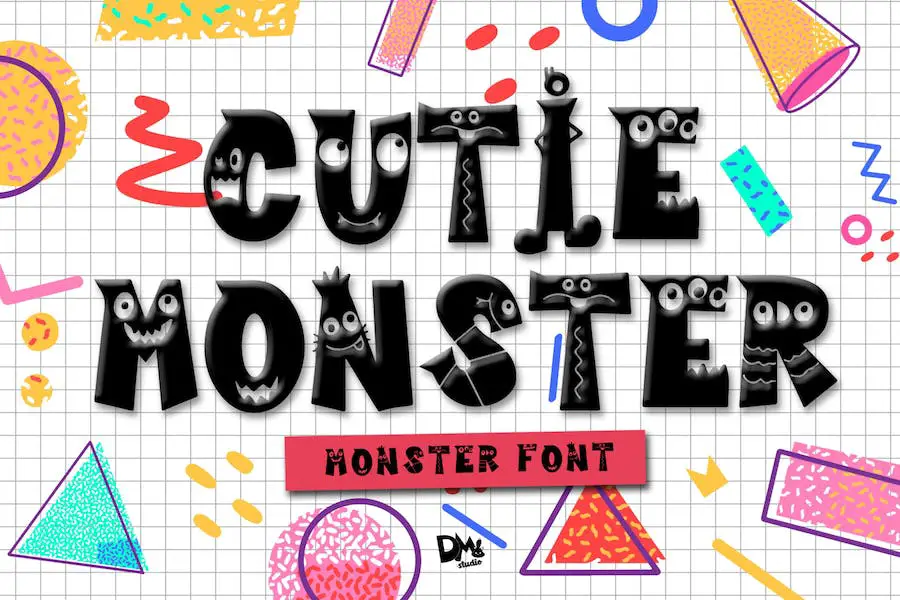
Cutie Monster 是一種令人愉悅且活潑的怪物字體,可為任何設計項目增添額外的魅力。 無論您是創建派對卡片、橫幅還是壁紙,這種字體都會帶來俏皮且富有表現力的氛圍。 它也非常適合製作手工藝品和宣傳材料。
最好的部分是它非常易於使用,不需要任何額外的軟件。 Cutie Monster 專為滿足您的創意需求而設計。
這款 Adobe Monster 字體有大寫和小寫兩種形式,允許您混合搭配,為您的設計創造完美的外觀。 憑藉其可愛有趣的風格,它添加了獨特而引人注目的元素,一定會給人留下深刻的印象。
Cutie Monster 的多功能性使其適用於從兒童材料到專業設計的各種項目。
友好的怪物
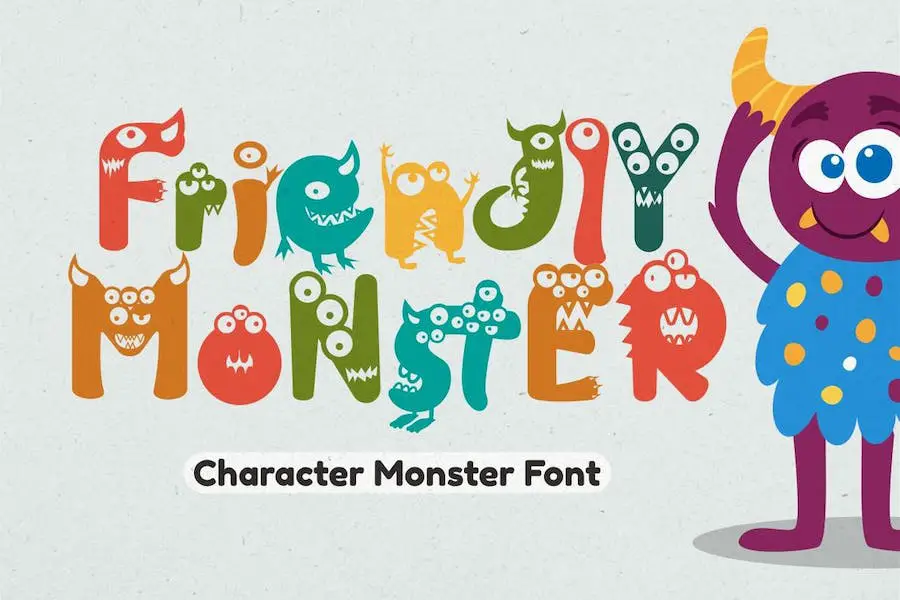
Friendly Monster 是一種角色怪物字體,可為您的設計項目增添歡快的感覺。 它非常適合海報、服裝、徽標、引言、專輯封面、書籍、名片等。
儘管其主題令人毛骨悚然,但 Word 的 Monster 字體具有嚴格的風格,使其易於閱讀和應用。 無論您是在尋找可愛、可愛還是友好的東西,Friendly Monster 都能讓您的設計脫穎而出。
怪物Demit
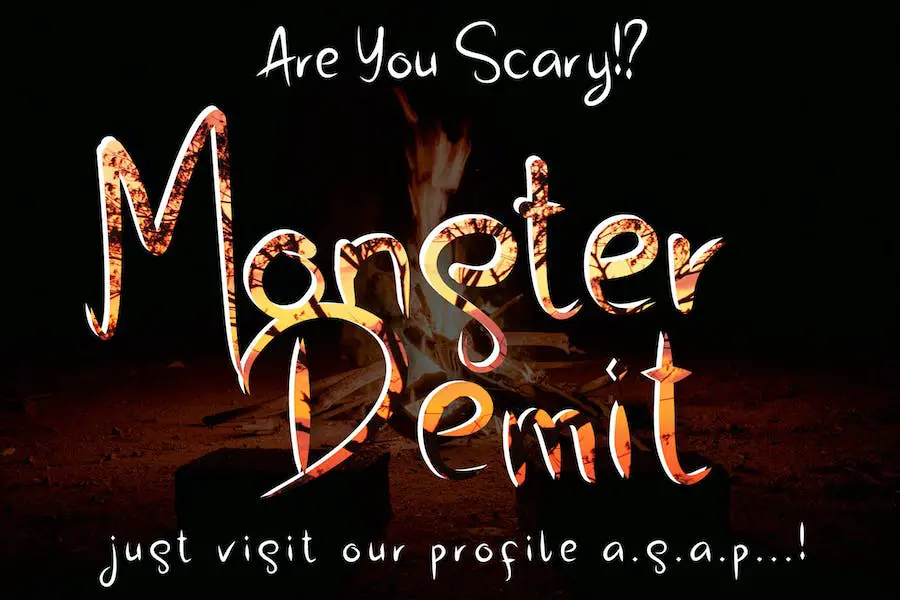
Monster Demit 是一種提供獨特而自然的觸感的字體,可以提升任何項目的水平。 這種字體被設計為可讀、優雅、時尚、吸引人,並且非常用戶友好。
Monster Demit 憑藉其時尚和專業的美學,是在品牌、設計、婚禮請柬、攝影、簽名、標誌設計、專輯封面、名片、報價和各種其他設計項目上創建水印的完美選擇。
無論您是專業的圖形設計師還是希望增強項目視覺吸引力的人,這款 Monster Fonts for Canva 都是一款不會讓人失望的字體。 它的多功能性和易用性使其成為您的字體集合的絕佳補充。
頑皮的怪物
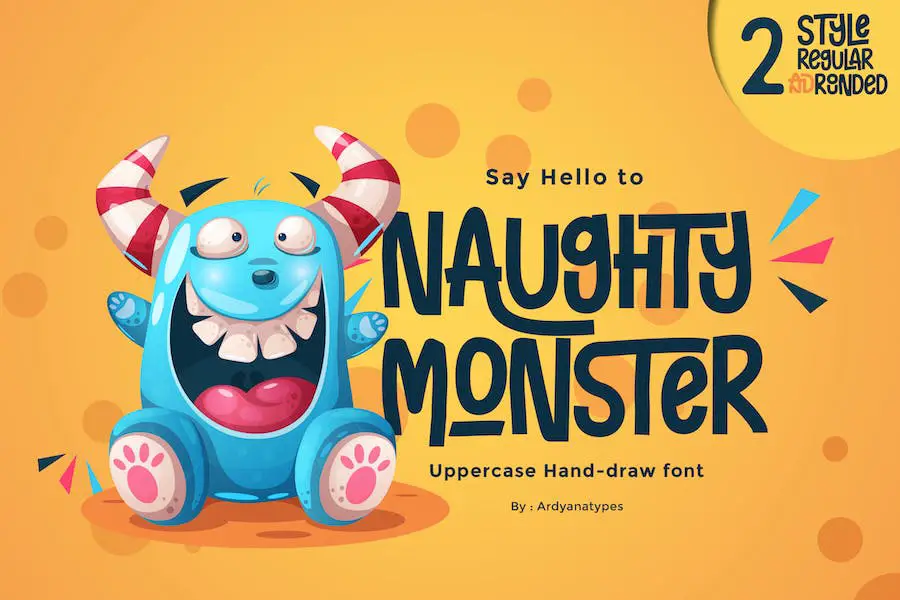
隆重推出 Naughty Monster,這是一種古怪而有趣的字體,旨在增強您所有的圖形設計項目。
憑藉其手工製作的美感和相互關聯的字符,該字體提供了獨特而迷人的魅力。 它具有 OpenType 功能,可自動將每個字符轉換為連字,從而創建獨一無二的外觀。
Naughty Monster 有兩種款式 - 常規款式和圓形款式 - 讓您可以選擇最適合您設計的款式。
Cricut 字體的 Monster 字體的突出特點之一是它能夠在嚴格的風格和歡快的印象之間取得完美的平衡。 這種獨特的組合使 Naughty Monster 不僅具有視覺吸引力,而且易於閱讀並融入到各種設計項目中。
怪物暗巢
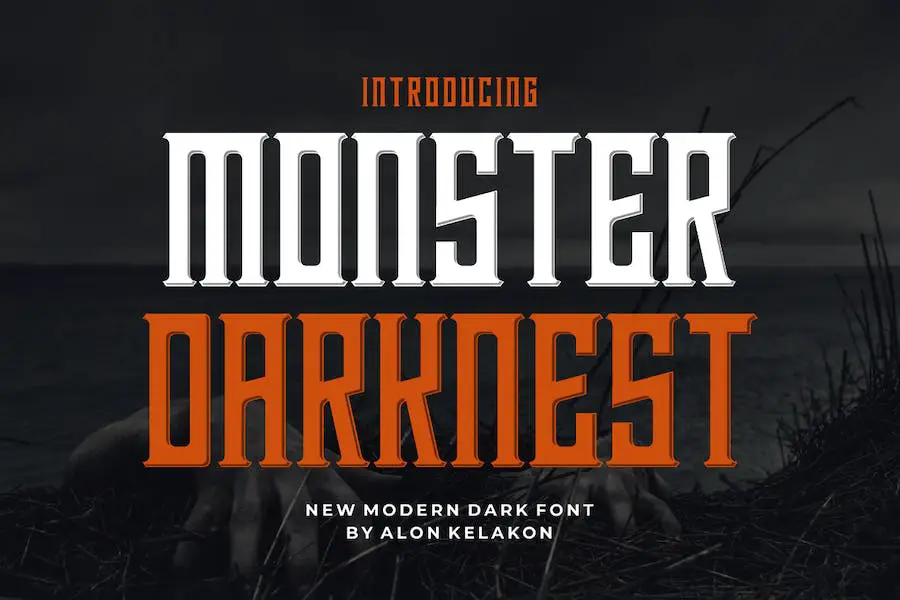
Monster Darknest 是一種獨特的字體,可以增強各種設計項目。 它非常適合標籤、服裝、電影場景、海報、電影標題、演出、專輯封面、徽標等。
憑藉其即用型功能,這款 Monster Tattoo 字體是任何圖形設計師工具包的寶貴補充。 其多功能性使其適用於廣泛的設計目的,讓您能夠創建引人注目且具有視覺吸引力的項目。
無論您是從事專業品牌項目還是個人創意工作,Monster Darknest 一定會將您的設計提升到一個新的水平。
怪物瘋狂
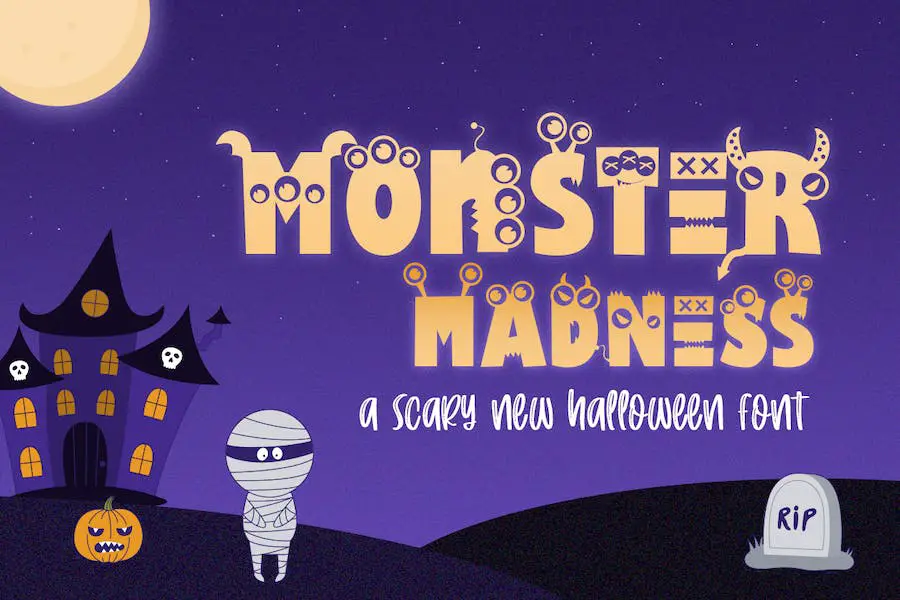
Monster Madness 是一種可以讓您的圖形設計項目變得栩栩如生的字體。 憑藉其 OTF 和 TTF 格式,您可以輕鬆地將它們合併到您的設計中。
無論您是在製作徽標、海報或網站,還是需要 Monster 字體來進行有趣和怪異的設計,Monster Madness 都可以為您的設計增添創意。 立即獲取並釋放您的創造力!
閃靈怪物
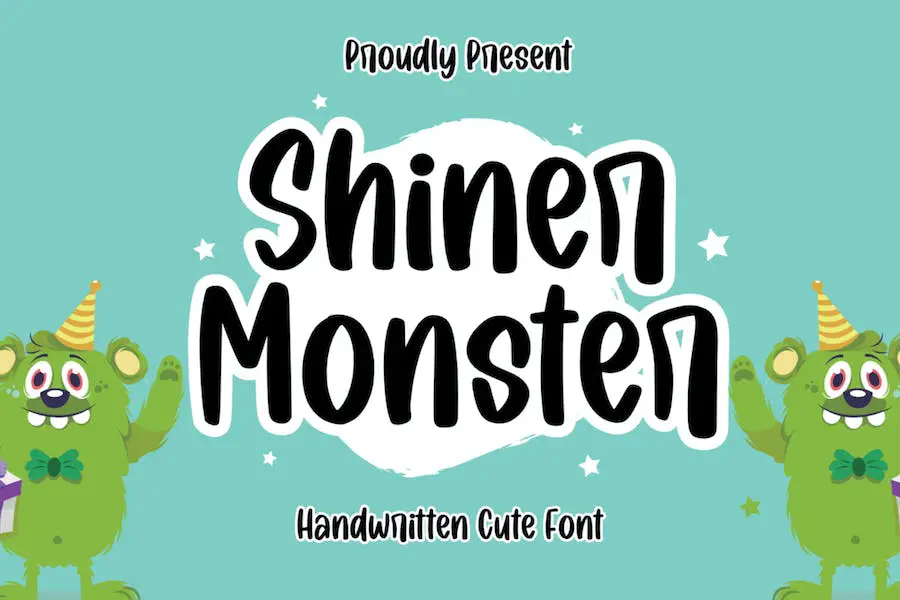
隆重推出 Shiner Monster Font – 一種可愛而古怪的手寫字體,一定會給您的設計項目帶來令人難以置信的愉悅感。
憑藉其大小寫字母、標點符號、數字和多語言支持,該字體提供了增強創造力所需的一切。 將 Shiner Monster Font 添加到您的設計中,觀看它們真正脫穎而出!
Shiner Monster Font 具有難以抗拒的迷人魅力。 其手繪風格為您的設計增添了獨特和個人的感覺,使它們更具吸引力和引人注目。
無論您是在製作徽標、海報、網站還是任何其他設計項目,此字體和此列表中的其他恐怖字體都會立即提升其美感並帶來一絲俏皮感。
蒙斯特里亞
Munsteria 具有基本的拉丁 AZ 和 az 字符、標點符號和數字,非常適合一系列項目,從在線遊戲到電影標題,從快餐菜單到雜誌設計,甚至 YouTube 封面和社交媒體頁面封面。
與傳統的可怕怪物不同,這款 Monster Energy 字體為該術語帶來了全新的定義。 這是一種以可愛、可愛和友好的怪物為特色的字體,非常適合兒童項目。 借助 Munsteria,您可以為您的設計增添一絲趣味和創造力。
梭子魚怪物
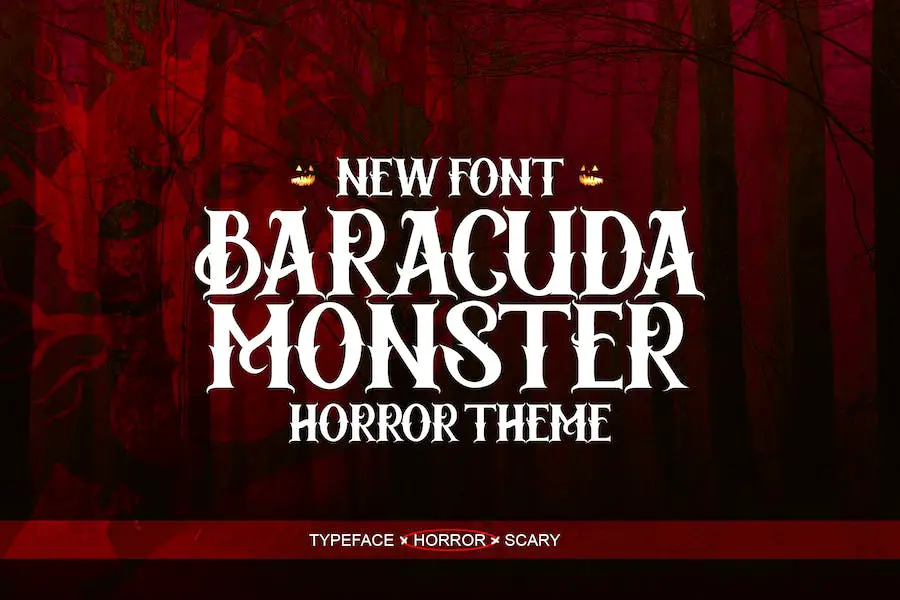
Baracuda Monster 是一種萬聖節風格的恐怖字體,可以為任何設計增添陰森恐怖的感覺。 該字體非常適合恐怖電影,但也可用於需要令人毛骨悚然的氛圍的其他項目。
該字體提供大寫和小寫字母,使您的設計具有多功能性。 通過其替代角色,您可以創建獨特且定制的外觀。 連字為您的文本增添了額外的精緻度和風格。
除了字母之外,Baracuda Monster 還提供數字和標點符號,確保您可以創建連貫且完整的設計。 Ghastly Panic 字體還支持多種語言,適合全球受眾。
怪物划痕
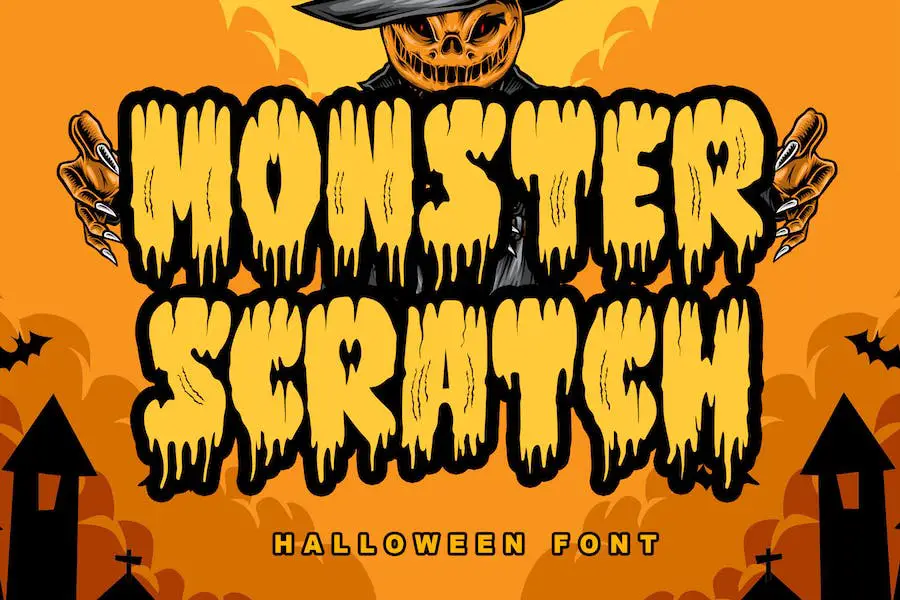
Monster Scratch 是一種顯示字體,可為您的萬聖節派對帶來怪異且令人難以置信的獨特觸感。
憑藉其 PUA 編碼,該字體允許您訪問其所有字形,使其非常適合為您的萬聖節工藝品、恐怖電影海報和任何其他需要令人難以忘懷的良好觸感的設計添加壯觀的外觀。
在 Monster Scratch 的幫助下將您的項目提升到最高水平。
托曼怪物
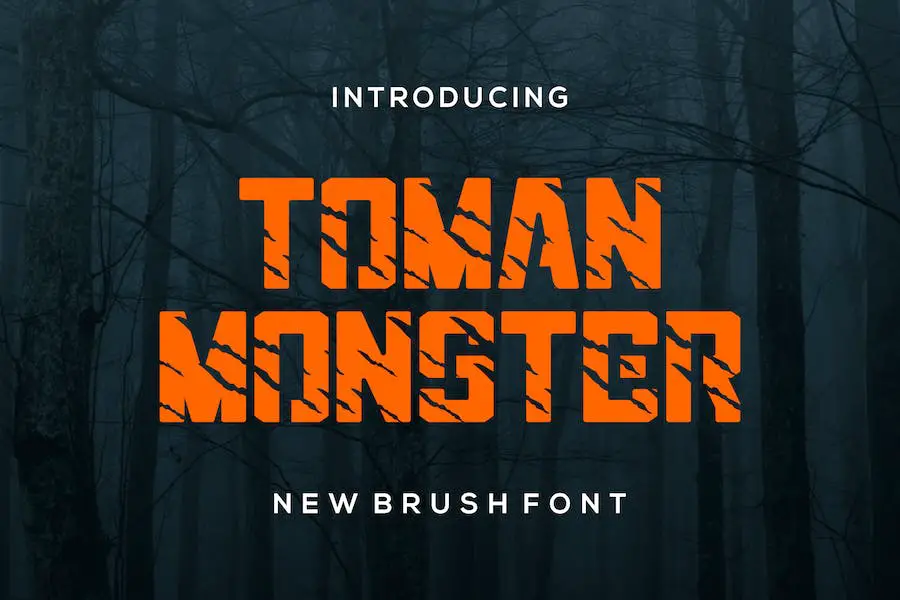
Toman Monster 是一種大膽而真實的顯示字體,可為您的圖形設計項目增添獨特性和創造力。
該字體具有現代而引人注目的風格,非常適合徽標、T 卹印刷、電子競技等。
無論您是從事品牌項目還是只是想增強藝術品的設計,Toman Monster 都是在任何環境下脫穎而出的多功能選擇。 是時候用這款出色的字體釋放您的創造力了!”
頭腦風暴
Brainseater 是一種令人難以置信的字體,可以徹底改變您的設計項目。 無論您是在設計雜誌標題、海報、徽標,甚至是 T 卹設計,這款字體都能滿足您的需求。
它還可用於字幕、名片、書籍封面、婚禮請柬等等。
《Brainseater》的一大特色是其細膩、優雅的書寫風格。 流暢的筆劃和漂亮的連字給您的文字帶來獨特的藝術感
這就像為每個字母添加一點創造力。 其結果是一種現代字體能夠立即吸引註意力並做出大膽的聲明。
你感到害怕
You Are Scared 是一款恐怖手寫字體,專為為您的萬聖節項目增添恐怖氣息而設計。
無論您是在製作徽標、品牌材料、賀卡、海報還是任何其他設計,這種字體都是營造令人毛骨悚然、令人難以忘懷的氛圍的完美選擇。
通過 You Are Scared,您可以通過其獨特而怪異的手寫風格將您的設計變為現實。 該字體捕捉了恐懼的本質,並為您的創作增添了一絲恐怖感。 它非常適合任何需要萬聖節主題改造的項目。
最好的免費怪物字體
希望為您的設計項目增添一些創意? 看看本文中介紹的最佳免費 Monster 字體就知道了。
準備好受到啟發,將您的排版提升到一個新的水平! 看看這些令人難以置信的字體並釋放您的創造力。
怪物
Monster 是一種非常適合希望增強其項目的圖形設計師的字體。 該字體由 Mozatype 創建,不僅功能強大,而且免費供個人使用。 借助 Monster,您可以將您的設計提升到一個新的水平,讓它們在人群中脫穎而出。
Monster 字體為您的項目帶來獨特的風格和風格,有助於吸引觀眾並給人留下持久的印象。
無論您是設計徽標、創建海報還是在網站上工作,這種字體都會增添一絲創造力和專業精神。
Monster 的一大優勢是它的多功能性。 該字體有各種樣式和粗細,讓您可以嘗試並找到最適合您的設計的字體。 從大膽而有影響力到優雅而精緻,Monster 擁有一切。
諾加納斯
Alit Design 的 Noganas 是一款出色的字體,它將把您的圖形設計項目提升到一個新的水平。
這種字體非常適合希望通過獨特且引人注目的字體來增強其項目的設計師。 憑藉其時尚而現代的設計,Noganas 一定會給人留下持久的印象。